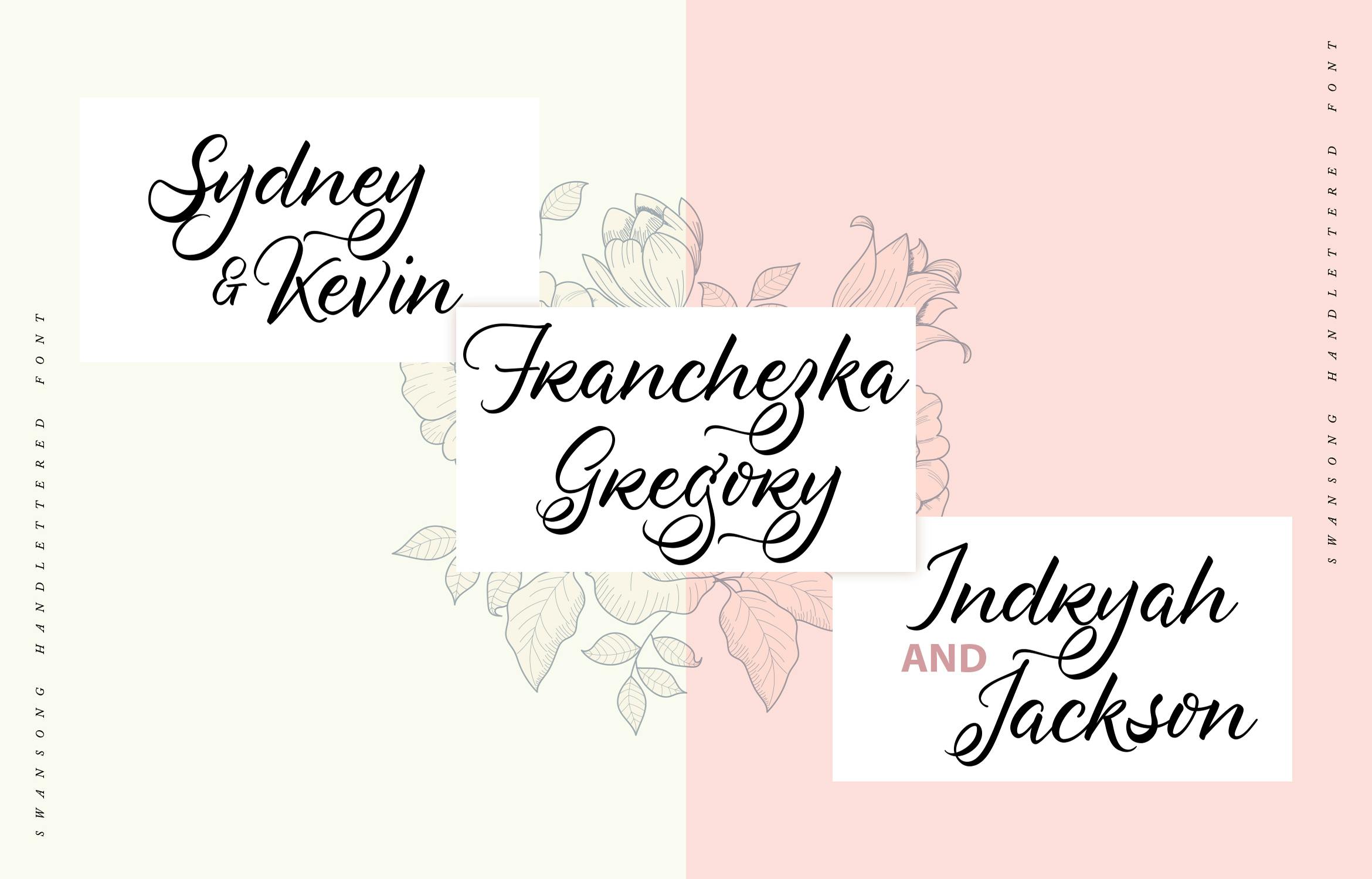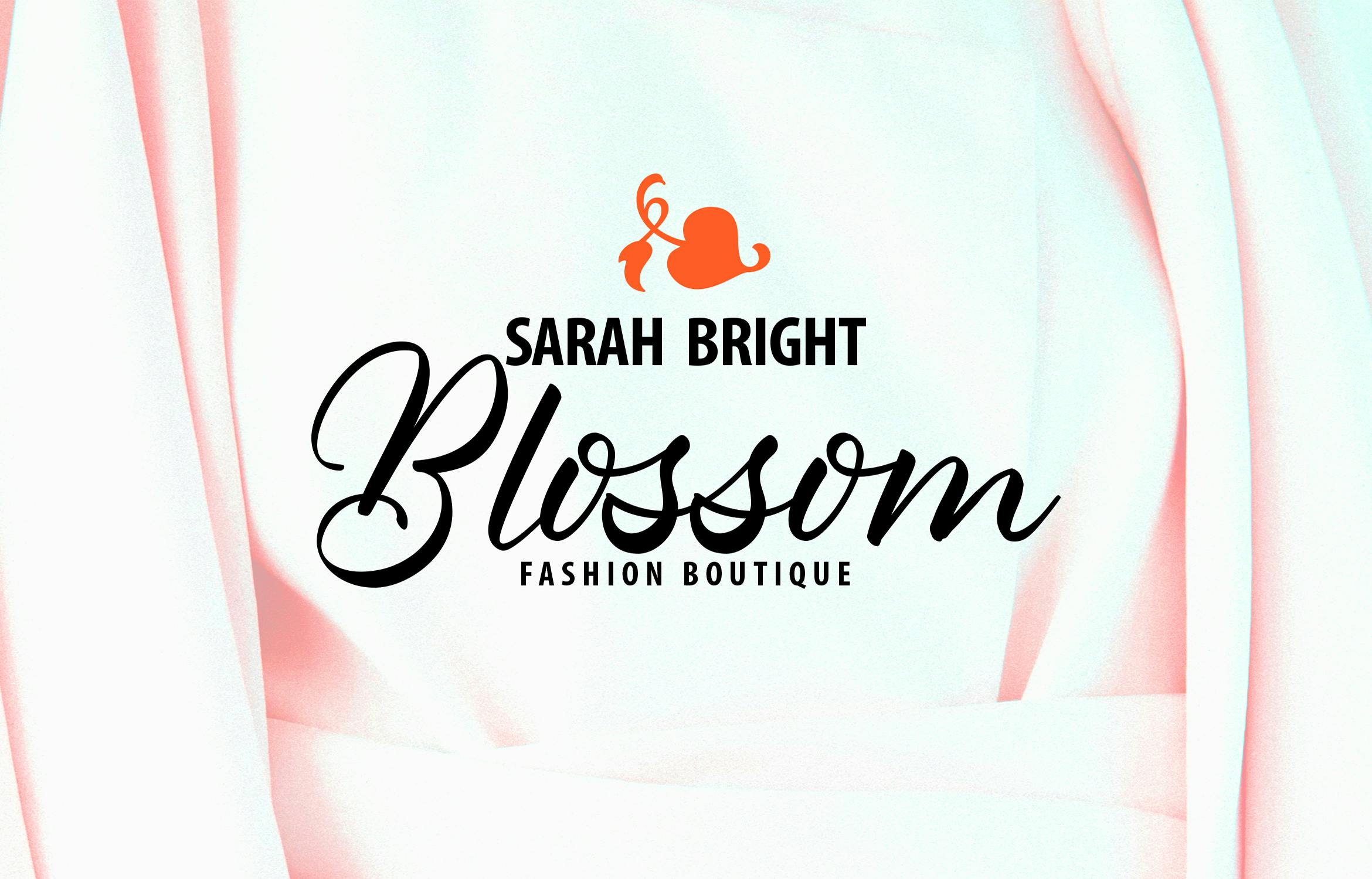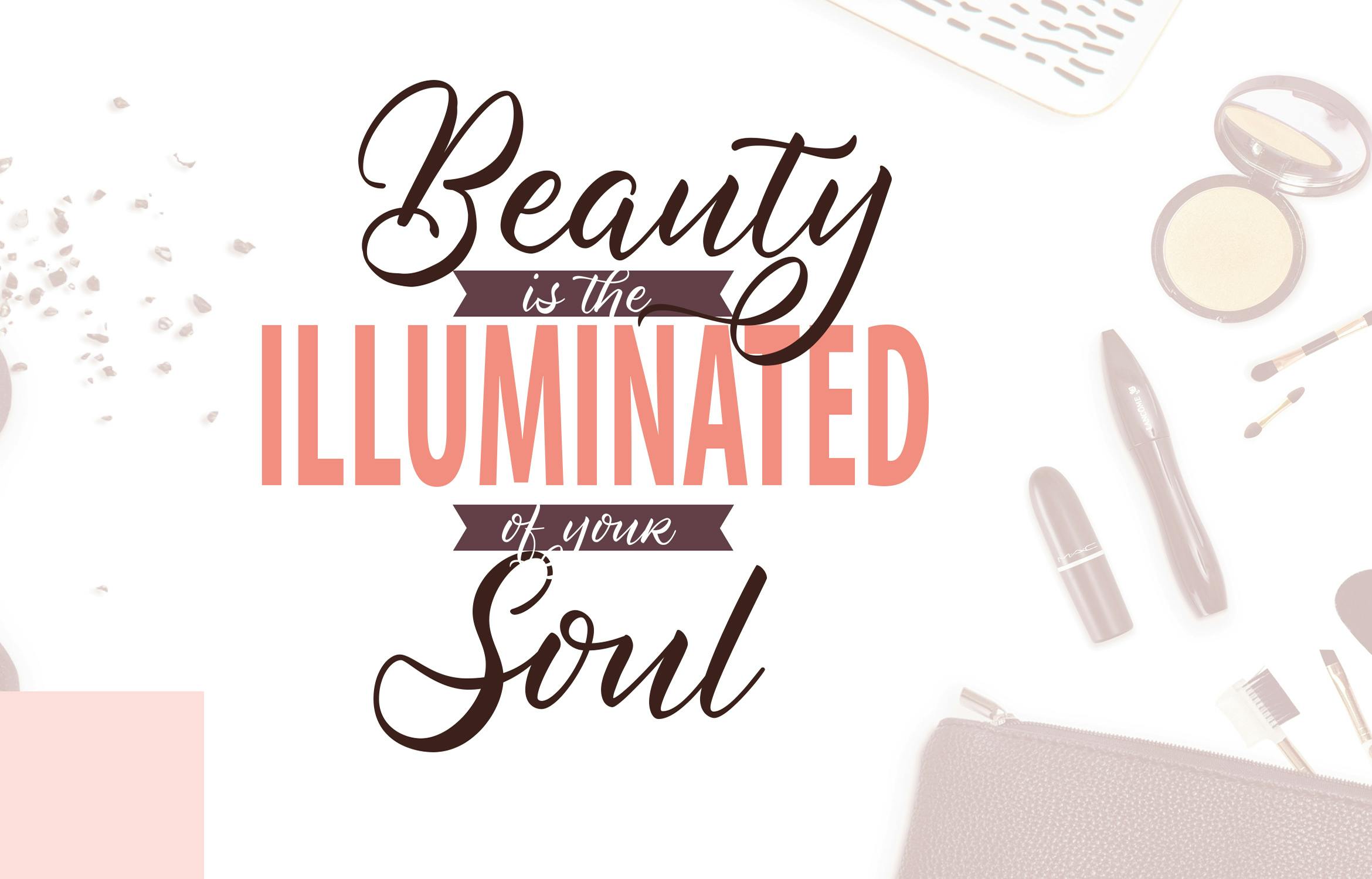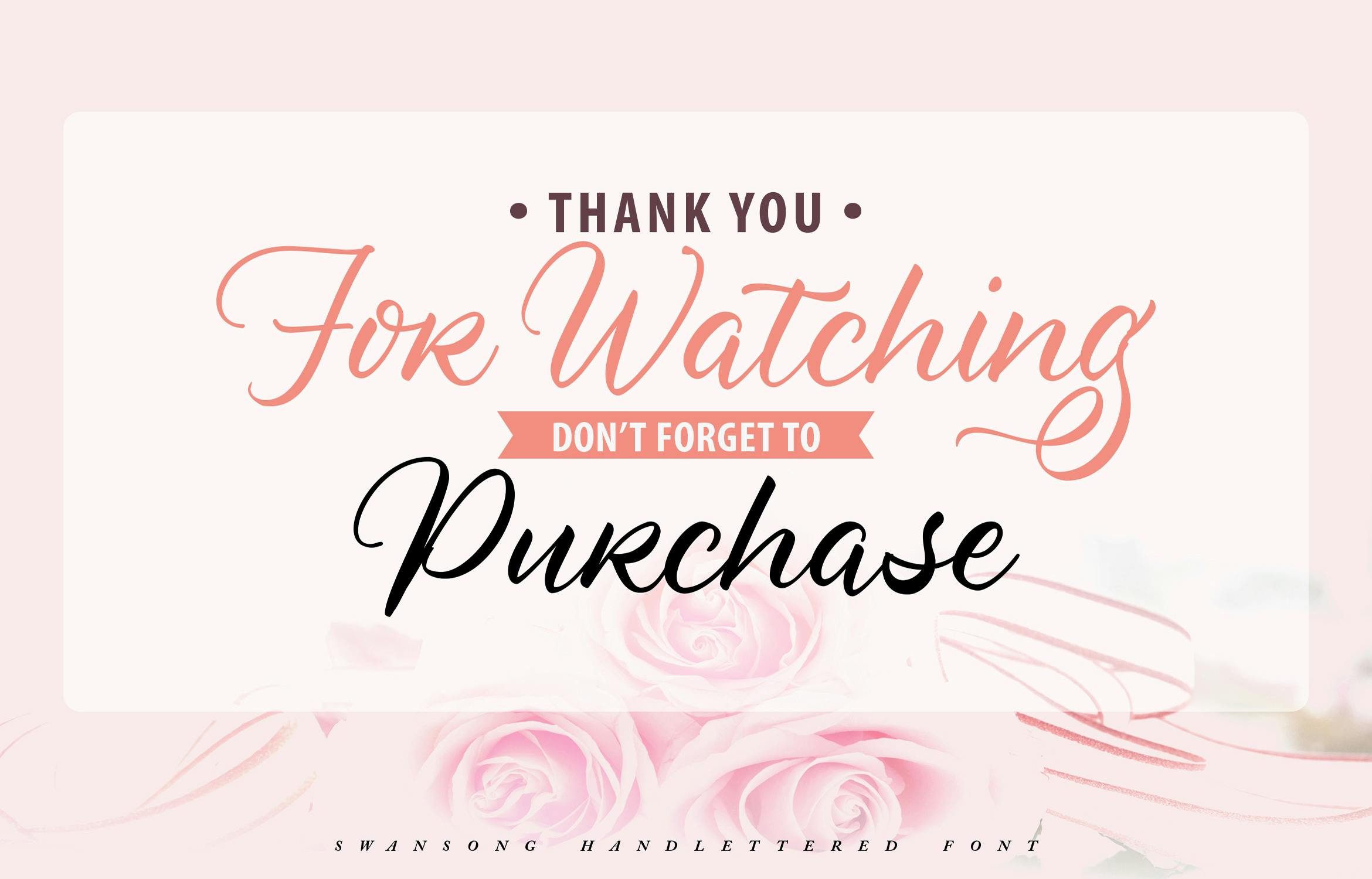
فونت Swansong | فونت خطاطی دستنویس با سبک خوشنویسی، بسیار زیبا برای طراحی دعوتنامهها، کارتهای تبریک، مواد برندینگ، کارتهای ویزیت، نقلقولها، پوسترها و موارد دیگر!
کاراکترهای جایگزین به چندین ویژگی Open Type تقسیم شدهاند مانند Stylistic Sets، Stylistic Alternates، Contextual Alternate، SWASH و Ligature. ویژگیهای Open Type را میتوان با استفاده از برنامههای کاربرپسند Open Type مانند Adobe Illustrator، Adobe InDesign، Adobe Photoshop، Corel Draw X و Microsoft Word دسترسی پیدا کرد. این فونت دارای کدگذاری PUA یونیکد (فونتهای مخصوص کدگذاری شده) است که به سادگی میتوان به تمامی کاراکترهای جایگزین دسترسی پیدا کرد.